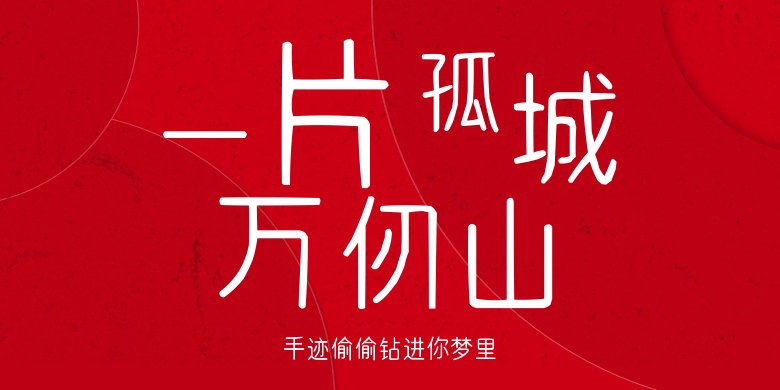
手迹偷偷钻进你梦里
手迹偷偷钻进你梦里,这款字体结构工整、笔画清晰,兼顾美观与易读性,适用于标题、正文、海报、包装、LOGO 等多种场景。字形优雅稳定,风格百搭耐看,适配日常排版与创意设计,让文字呈现更舒适、更具质感。手迹偷偷钻进你梦里一笔一画,皆是细节,以均衡的比例、流畅的线条打造舒适视觉体验,字形端正大气,风格简约现代。无论是商业设计、品牌宣传还是日常排版,都能轻松驾驭,让文字更有格调与力量。手迹偷偷钻进你梦里字体下载。